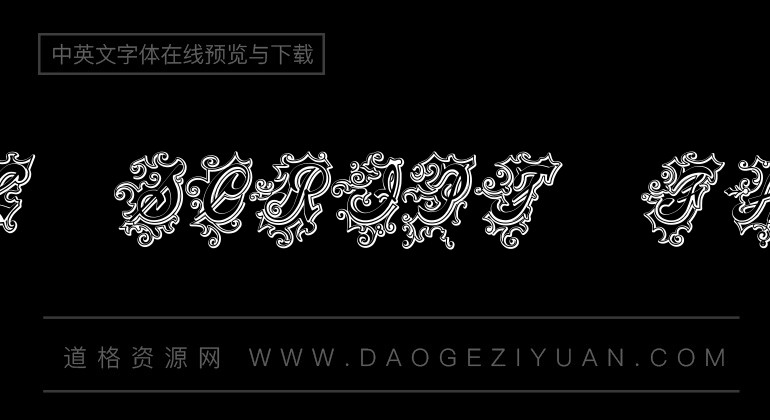
Centennial Script Fancy Three 是一种优美的手写字体,它具有华丽的线条和细节,适用于许多设计项目。该字体由设计师 Frederic W. Goudy 于 1940 年代创作,并在其生命周期内经历了多次改进和重新设计。 Centennial Script Fancy Three 的特点是其与众不同的字母形状。它的字母形状是古老的装饰性字体和现代手写字体的完美结合。它的笔画流畅,优美,更多的是一种艺术性的表达方式,而不是一种实用性的工具。 它的应用范围非常广泛,常用于书籍封面、海报、广告、名片、证书、菜单设计等方面。如果你正在寻找一种华丽且优美的字体,Centennial Script Fancy Three 可以是一个不错的选择。内容介绍
Centennial Script Fancy Three是一款非常不错的手写艺术字体,具有很好的视觉感,适合于文化类的宣传设计、商业类品牌的广告和产品包装设计以及个性化文字排版等较多场景。